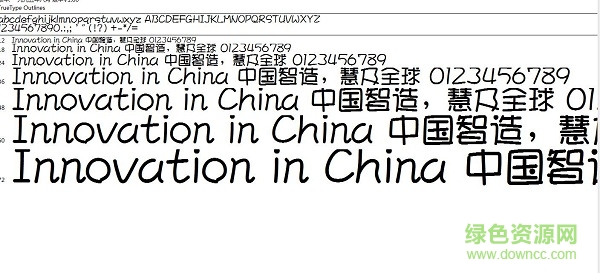
經(jīng)典簡(jiǎn)隨意
經(jīng)典簡(jiǎn)隨意字體是一款類似手寫體的中文字體,線條流暢,秀美柔和,親切感強(qiáng),具有獨(dú)特氣質(zhì),可以廣泛應(yīng)用于廣告、包裝、海報(bào)等方面,喜歡這款字體的朋友快來(lái)下載吧!
經(jīng)典簡(jiǎn)隨意字體